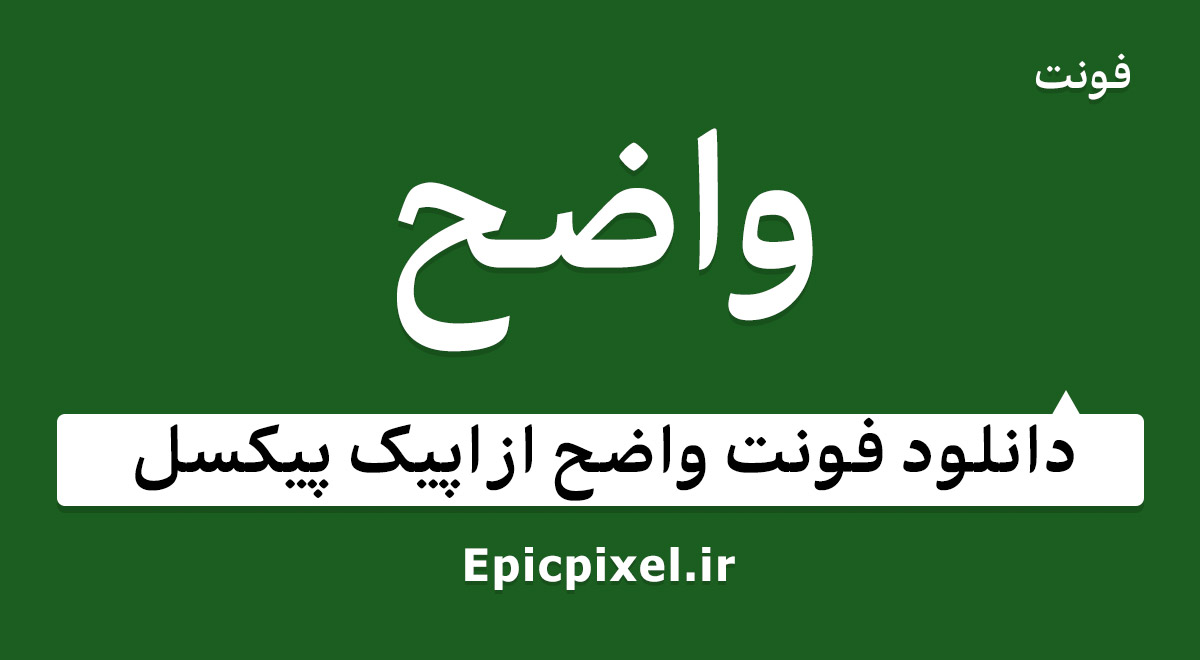
3 فونت واضح فارسی
اگر به دنبال فونتی هستید که خوانایی متون قرآنی را افزایش دهد و در عین حال زیبایی بصری داشته باشد، فونت قرآنی واضح فارسی گزینه ای ایده آل است. این فونت با طراحی منحصر به فرد خود، تجربه خواندن قرآن را بهبود می بخشد. یکی از ویژگی های برجسته این فونت، سادگی و وضوح آن است که باعث می شود حتی در اندازه های کوچک نیز به راحتی قابل خواندن باشد؛ این ویژگی به ویژه برای استفاده در صفحات وب و اپلیکیشن های موبایل بسیار مهم است.
طراحی فونت واضح بر پایه هنر ایرانی و سلیقه فارسی زبانان شکل گرفته و با روحیه ایرانی سازگار است. این فونت با اعراب گذاری دقیق و تایپوگرافی مناسب تک تک کلمات قرآن (بیش از ۲۱ هزار کلمه)، به درک صحیح آیات کمک می کند. این ویژگی برای کسانی که به دنبال مطالعه دقیق و تدبر در قرآن هستند، بسیار ارزشمند است. همچنین خطی ساده، امروزی و منحصر به فرد داشته و در فضای دیجیتال بسیار سازگار است.
از مزایای دیگر این فونت، رایگان بودن آن است که دسترسی همگان را به آن آسان می کند. این فونت برنده جایزه TDC از امریکا (معتبرترین جایزه بین المللی فونت دنیا) شده است که نشان از کیفیت بالای طراحی آن دارد. با این حال، ممکن است این فونت برای چاپ در ابعاد بسیار بزرگ به دلیل تمرکز بر وضوح در ابعاد کوچک، بهینه نباشد. در مجموع، فونت قرآنی واضح فارسی با تلفیقی از زیبایی، خوانایی و دقت، انتخابی مناسب برای استفاده در پروژه های قرآنی شماست.